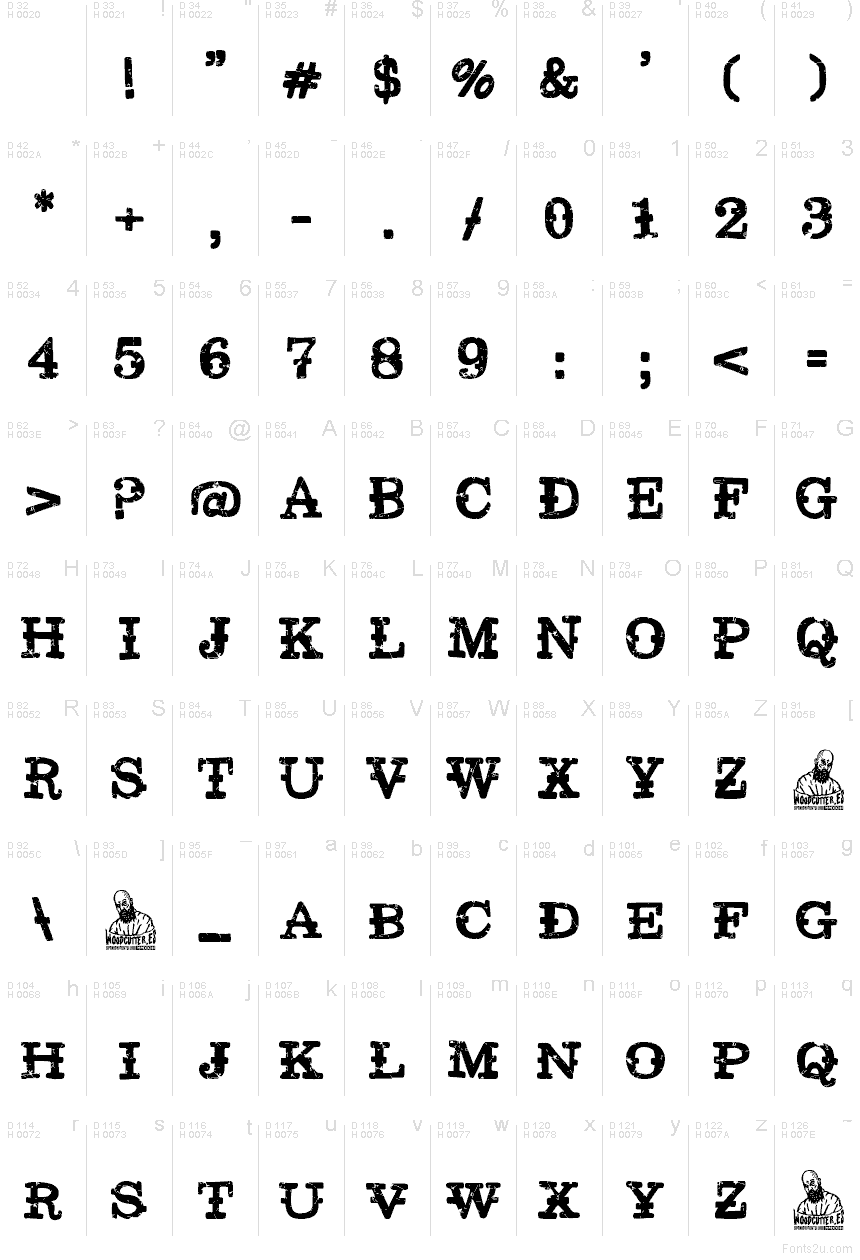
La Prestigiosa autorstwa Woodcutter Manero to darmowy krój pisma typu western, który oddaje surowy charakter dawnych szyldów z Dzikiego Zachodu. Wielkie litery są szerokie, masywne i mocno sfatygowane – z wyszczerbionymi krawędziami, stępionymi szeryfami i zniszczoną teksturą, dzięki czemu wyglądają, jakby zostały odciśnięte na deskach saloonu czy starych, wystawionych na próbę czasu plakatach.
To naturalny wybór na etykiety whisky, plakaty rodeo, rustykalny branding restauracji, ulotki festiwalowe czy plansze tytułowe, które mają oddawać zakurzony klimat XIX wieku. Jako darmowy font świetnie sprawdzi się również w krótkich hasłach, monogramach i dużych inicjałach, gdzie porysowana powierzchnia i solidna sylwetka liter szybko przyciągają wzrok.